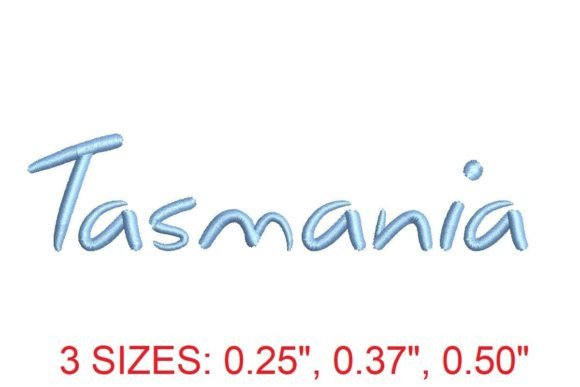
Tasmania Font
Trouver les bons éléments de conception peut être un défi, mais Tasmania Font propose une collection exceptionnelle qui rehausse instantanément votre travail.
Que vous créiez des produits POD (impression à la demande), des invitations de mariage ou des visuels pour les réseaux sociaux, Tasmania Font est un choix idéal.